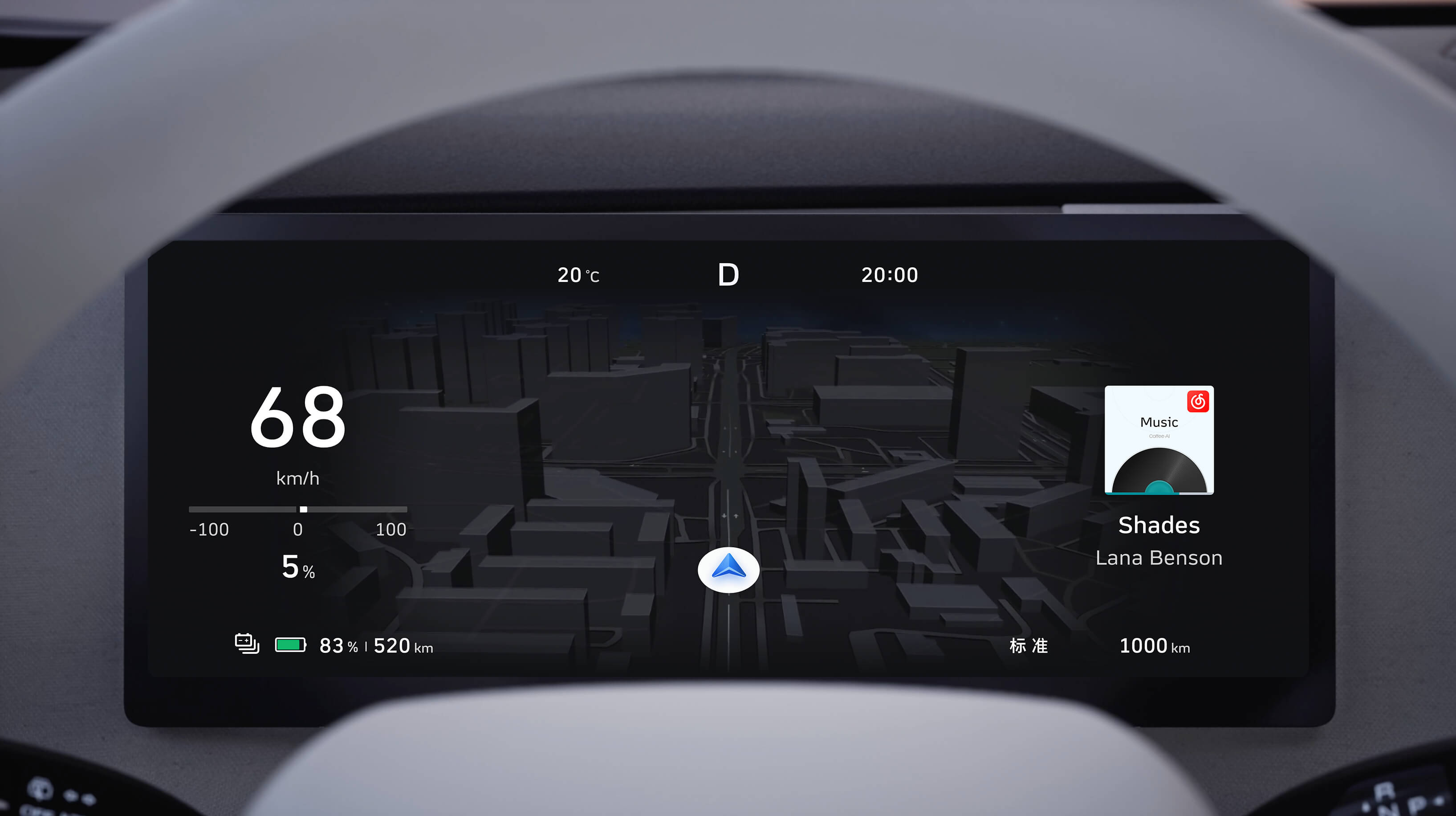
长城共享体GWM Sans全球开放商用---专为车载系统设计的中文字体,这款字体结构工整、笔画清晰,兼顾美观与易读性,适用于标题、正文、海报、包装、LOGO 等多种场景。字形优雅稳定,风格百搭耐看,适配日常排版与创意设计,让文字呈现更舒适、更具质感。长城共享体GWM Sans全球开放商用---专为车载系统设计的中文字体一笔一画,皆是细节,以均衡的比例、流畅的线条打造舒适视觉体验,字形端正大气,风格简约现代。无论是商业设计、品牌宣传还是日常排版,都能轻松驾驭,让文字更有格调与力量。长城共享体GWM Sans全球开放商用---专为车载系统设计的中文字体字体下载。
一款车机屏幕中「易于阅读」的系统字体
「专为车载系统设计的中文字体」
字体不单是内容直观传递,更涉及安全驾驶识别。一般来说,传统字体较适用移动端,但往往忽视车载环境的特殊需求,导致文字易认性不足,从而影响驾驶安全体验。
针对传统车载字体在车机环境下的局限性,长城汽车携手蒙纳字库,以驾驶安全和用户体验为出发点,历时2年精心打造了全球“长城共享体”。这套字体秉承“安全、高效、自然”的设计理念,巧妙兼容圆润不失力量感的设计,车载阅读无压力。其设计不仅使整体界面更加时尚、年轻化,还大幅提升了易读性和辨识度,从而显著增强了车载界面的安全性和舒适感。
「长城共享体设计说明」
平衡汉字与拉丁字符内部、外部、横向、纵向上的空间,让文字更有呼吸感
结合中式美学的中宫微调,简洁、等粗的笔画,开放的书写骨架
整体风格年轻化、现代化,刚柔并济,兼顾更多车型
字体作为信息传递的重要载体,除了安全识别阅读,也兼并着美学设计。为解决多品牌、多车型场景下字体应用不统一带来的品牌形象碎片化问题,同时提升全球用户的驾驶阅读体验,长城汽车决定倾力打造一款适合车机屏幕阅读的字体。车载屏字体并非单纯追求美观,而是以安全为核心,兼顾品牌、技术和用户体验的系统化设计策略。这一举措反映了汽车行业从“功能驱动”向“体验驱动”的转变,也体现了中国品牌在细节创新上的深入探索。
「长城共享体三大核心目标」
1. 安全易读针对车载屏幕界面进行深度优化,确保在任何光照与尺寸下均具备匹配的易读性与舒适度
2. 减少阅读时长行驶中能快速识别信息,提升驾驶安全
3. 提升设计美学遵循经典黑体结构的基础上,融入体现长城汽车“科技、硬朗、可靠”品牌调性的设计细节,形成独特的视觉基因
长城汽车与蒙纳携手共创【长城共享体】,在不断完善和更新GWM Sans,使得用户在车机行驶时更舒适、安全的阅读信息,自正式发布以来,得到广泛关注与好评,成为第一家车载中文字体设计的车企。2023年荣幸获得了Hiiibrand第14届品牌定制字体的国际奖项,分别是“优秀品牌奖”及“设计优异奖”。